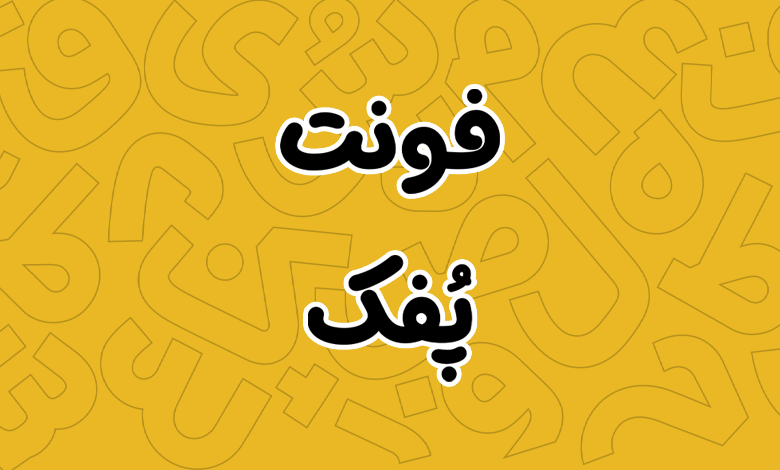
فونت پفک (Pofak)
فونت پفک (به انگلیسی: Pofak) فونتی دستنویس با ساختاری صمیمی و خوشمزه است که از دنیای نوستالژیک وارد دوره مدرن امروزی شده است. از این فونت میتوانید برای تبلیغات، عناوین و بستهبندی محصولات بهترین استفاده را داشته باشید. فونت پفک رایگان نیست و در سه بسته متفاوت از لحاظ وزنی و وریبل عرضه شده است.
مسلم ابراهیمی این فونت را با الهام از ساختار پفک نمکی طراحی کرده است که از حروف جایگزین نیز پشتیبانی میکند. توسعه این فونت نیز توسط ماهان جعفرزاده انجام گرفته است که میتوانید در محیطهای مختلف سیستم عامل، نرمافزاری و وب از این قلم استفاده کنید. در ادامه به نقد و بررسی کامل این فونت فارسی میپردازیم.
فونت پفک با الهام از حس و حال نوستالژیک پفک نمکی، روحی شاداب و بازیگوش به طراحیهای شما میبخشد. این فونت دستنویس، برخلاف ظاهر آزادش، با دقت و وسواس طراحی شده است.
خطوط نرم و منحنیهای دلنشین آن، حسی صمیمی و دوستانه القا میکنند، اما این صمیمیت به هیچوجه به معنای سادهانگاری نیست. فونت پفک با ساختاری هندسی و متعادلش، در اندازههای کوچک هم خوانایی فوقالعادهای دارد. این ویژگی آن را به گزینهای ایدهآل برای متون طولانی، مانند توضیحات روی بستهبندی یا محتوای کتابهای کودک، تبدیل کرده است.
سبک طراحی فونت pofak، ترکیبی از سنت و مدرنیته است. حس نوستالژیک آن یادآور دستخطهای قدیمی و خاطرهانگیز است، اما وزنهای متنوع و امکانات مدرن OpenType، آن را به یک ابزار حرفهای برای طراحان امروزی تبدیل میکند. اگر میخواهید طرحهایتان همزمان حس صمیمیت و حرفهایگری را منتقل کنند، پُفک مثل یک دوست قدیمی است که با ظاهری تازه و شیک به ملاقات شما آمده!
انعطاف و کاربردپذیری فوقالعاده
یکی از نقاط قوت فونت پفک، پشتیبانی از ۹ وزن متنوع آن است که شامل وزنهای سبک و نازک تا سنگین و متغیر است. این تنوع به شما امکان میدهد که برای هر نوع پروژهای، از متون ریز و خوانا گرفته تا تیترهای تبلیغاتی بزرگ و چشمگیر، فونتی متناسب داشته باشید.
وزنهای سبکتر برای متون طولانی مثل توضیحات محصول یا محتوای وبسایتها عالی هستند، در حالی که وزنهای سنگینتر برای عناوین تبلیغاتی، لوگوها و جلد کتابها ظاهری جذاب و نمایشی دارند.
پشتیبانی از زبانهای فارسی، عربی و انگلیسی، همراه با اعداد فارسی و عربی هکشده، پفک را به یک فونت چندزبانه تبدیل کرده است. این قابلیت بهویژه برای برندها و محصولاتی که در بازارهای بینالمللی فعالیت دارند، یک مزیت بزرگ است. اعداد هکشده فارسی و عربی بهگونهای طراحی شدهاند که کاملا با ساختار حروف هماهنگ باشند و ظاهری یکپارچه و زیبا ایجاد کنند.
همچنین در بخش اعداد شاهد ارائه نسخه مخصوص اعداد فارسی هک شده از فونت هستیم که برای همه زبانها از اعداد فارسی استفاده شده است. یا در نسخه مخصوص بدون حروف لاتین که خبری از اعداد و حروف لاتین نبوده و تنها ساختار فارسی و عربی فونت را شامل میشود. این نسخه از فونت پفک برای توسعه نرمافزاری یا استفاده در وبسایت کاربرد دارد.
جادوی خلاقیت با حروف جایگزین و نسخه وریبل
یکی از جذابترین ویژگیهای فونت پفک، مجموعهای گسترده از حروف و ترکیبات جایگزین آن است که آزادی عمل شما را در پیادهسازی طرحهای خلاقانه فراهم میکند. این فونت بهصورت پیشفرض جایگزینهای خودکار را فعال میکند، اما برای کنترل بیشتر، تنظیمات OpenType در نرمافزارهایی مانند فتوشاپ به شما اجازه میدهند تا شکل حروف زیر را تغییر دهید:
- «و»
- «سش»
- «ههه»
- «حخجچ»
- «کگ»
- «ی»
نسخه وریبل فونت پفک علاوه بر اینکه شامل تنوع بالایی از وزنهای این قلم است، به شما اجازه میدهد اعداد انگلیسی را به فارسی تبدیل کنید، تراز عمودی آنها را تنظیم کنید یا حتی در لیستها از اعداد همعرض استفاده کنید.
این ویژگیها بهویژه در طراحیهای حرفهای مثل بستهبندی یا پوسترهای تبلیغاتی، جایی که جزئیات کوچک تفاوتهای بزرگ ایجاد میکنند، بسیار کاربردی هستند. با فونت پفک، هر حرف و عدد میتواند به یک اثر هنری کوچک تبدیل شود!
علاوه بر ترکیبات جایگزین، گلیفهای واحد پولی «تومان، ریال» در این فونت وجود دارد که میتوانید برای جلب توجه بیشتر از آنها استفاده کنید. این گلیفهای متفاوت برای واحد پولی باعث افزایش نرخ تبدیل در فروش محصولات خواهد شد.
فونت پفک؛ از صنعت چاپ تا بستهبندی محصولات
فونت پُفک به معنای واقعی کلمه یک فونت همهکاره است. فونتی «خوشخوراک» که کاملا برازندهاش است! این فونت برای هر پروژهای که نیاز به لحنی صمیمی، شاد و غیررسمی دارد، ایدهآل است.
در بستهبندی محصولات، بهویژه برای خوراکیها، اسباببازیها یا محصولات کودک و نوجوان، پفک با ظاهر بازیگوش و خوانایش، توجه مخاطب را جلب میکند و حس خوشایندی به برند شما میبخشد.
در تبلیغات، چه برای بنرهای دیجیتال و چه بیلبوردهای شهری، وزنهای سنگینتر پفک تیترهایی جسور و جذاب خلق میکنند که در ذهن مخاطب ماندگار میشوند.
برای طراحی جلد کتاب، پفک میتواند انتخابی عالی برای کتابهای کودک، رمانهای طنز یا حتی آثار انگیزشی باشد که میخواهند پیامی جدی را با لحنی دوستانه منتقل کنند. همچنین، در محتوای دیجیتال مثل پستهای اینستاگرام یا وبسایتهای خلاقانه، پفک به دلیل خوانایی بالا و حس صمیمانهاش، تجربه کاربری را بهبود میبخشد.
پفک فقط یک فونت نیست؛ یک ابزار خلاقانه است که به شما کمک میکند داستان برند یا پروژهتان را با طعمی متفاوت روایت کنید. این فونت با ترکیب هوشمندانهای از نوستالژی و مدرنیته، انعطافپذیری بینظیر و خوانایی فوقالعاده، به طراحان اجازه میدهد تا طرحهایی خلق کنند که هم حرفهای باشند و هم دلنشین.